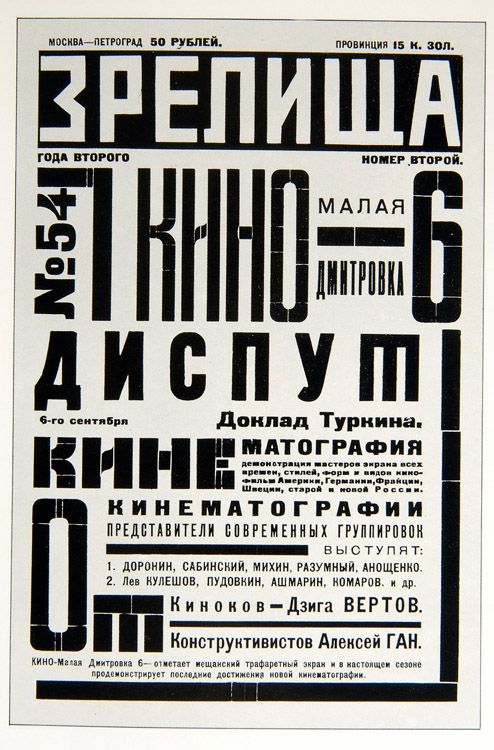
Советский леттеринг или шрифтовые композиции. Основные особенности | Русский Дизайн
Нас часто спрашивают: есть ли какие-то советские книги по советским рукописным шрифтам? На что мы неустанно отвечаем: нет, вернее были попытки что-то такое разработать Снарским, но безуспешные. А тем временем в этом нет ничего сложного и шрифты эти можно разбить на несколько групп. Конечно, новичку может показаться, что все они очень похожи, но это не так. Попробуем же сделать эту неблагодарную работу и рассмотреть каждую. Все названия будут условны, для усиления этой необходимой разницы между ними. Мы рассмотрим не все шрифты, но попытаемся выделить самые характерные и потому востребованные и в наше время.
1. Первая условная группа – «Классический». Такой шрифт больше всего напоминает рукописный. В частности он использовался в титрах кинофильма «Мимино». В остальном, чаще всего встречается в оформлении сталинской эпохи, выполняется тонкой кистью или пером.
2. Пользуется наибольшей популярностью, мы называем его «плакатным», т.к. выполнялся он в советские времена специальным плакатным пером представляющим собой плоскую металлическую пластинку и дающую толщину и остроту буквам.
Советский леттеринг или шрифтовые композиции. Основные особенности3. «Плакатный» жирный.
Советский леттеринг или шрифтовые композиции. Основные особенности4. «Округлый» шрифт. Такой мог встречаться на различных этикетках вин, на коробках шоколадных конфет и проч. Мог выполняться тонкой или средней колонковой кистью.
Советский леттеринг или шрифтовые композиции. Основные особенности5. «Неоновый». Чаще всего использовался в качестве вывесок универмагов, кинотеатров и проч. Эскизы такого могли выполняться обычной ручкой, реже пером.
Советский леттеринг или шрифтовые композиции. Основные особенности6. «Неоновый вертикальный». Применение такого, пожалуй, было даже шире, встречался и в книжках. Хотя с эстетической точки зрения он явно проигрывал первому.
7. «Промышленный». Применялся чаще всего для бытовой техники. Мог выполняться плакатным пером, однако с таким движением руки, чтобы толщина сохранялась одинаковой.
Советский леттеринг или шрифтовые композиции. Основные особенности8. «Плакатный прямой». Состоит из наклонных ровных полос и образующих буквы. Комбинированный шрифт по сути, часть выполняется плакатным пером, а какие-то буквы выводятся средней кистью.
Советский леттеринг или шрифтовые композиции. Основные особенности9. «Книжный». Распространение его было не таким широким, как у предыдущих. Это неудивительно, его очень сложно подвести под определение – рукописный. Такие шрифты встречались разве что в книжных иллюстрациях, титрах мультипликационных фильмов.
Дело в том, что воспроизвести его сразу не получится, какие-то детали придется доводить отдельно тонкой кистью, пером, ручкой.
Ну и нельзя не сказать о шрифтах, которым сложно дать какое-то определение, их следовало бы назвать декоративными, а некоторые из них, мы бы даже охарактеризовали, как шрифты с композиционными и прочими ошибками. А таких, между тем, не менее половины от встречающихся и по сей день на этикетках и вывесках. Но нельзя забывать и о том, что, скажем, тем рисунок и особенно живопись и отличаются от фотографии, тем и ценна она – некоторым несоответствием жизни, ее неизбежным искажением. Фотореалистичное же искусство многие профессионалы таковым не считают и это, пожалуй, справедливо. Так и шрифтовыми композициями занимаются чаще всего профессиональные художники. И порой даже нельзя объяснить, почему тот или иной шрифт прекрасен, сказывается профессиональное чутье.
Советский леттеринг или шрифтовые композиции.
Основные особенностиСоветский леттеринг или шрифтовые композиции. Основные особенностиСоветский леттеринг или шрифтовые композиции. Основные особенностиСоветский леттеринг или шрифтовые композиции. Основные особенностиСоветский леттеринг или шрифтовые композиции. Основные особенностиСоветский леттеринг или шрифтовые композиции. Основные особенностиСоветский леттеринг или шрифтовые композиции. Основные особенностиНу и попробуем ответить на вопрос, можно ли научиться леттерингу. Нет, нельзя, потому что слова такого нет, но можно научиться составлять шрифтовые композиции. Более того, убеждены, что все рассмотренные шрифты рано или поздно будут разработаны и доступны для общего пользования. Достаточно вспомнить, что шрифт «Кока-Кола» имеется в общем доступе со всеми заглавными и прописными буквами.
«Народная» типографика. Использование шрифтов в плакатах xx века [Курсовая №33781]
Содержание:
Введение
Хотя в наше время, по сравнению с прошлым веком, существует гораздо больше средств передачи информации, плакатная типографика до сих пор остается востребована. Во время нахождения человека за пределами жилища телевизионные, радио и интернет-каналы как правило становятся мало применимы, и в бой выходят плакатные объявления. Идя на работу, в спортзал или просто прогуливаясь, нам не спрятаться от пытливых взоров рекламных билбордов и социальных плакатов.
Хоть в наше время плакаты сильно изменились и часто выступают на электронных носителях, они все еще основываются правилах, заложенных в XX веке. Давайте же для начала посмотрим на историю плакатной типографии XX века
Глава 1История печатной рекламы в РоссииПервая печатная реклама появилась в газете “Санкт-Петербургские ведомости”, издававшийся академией наук в 1728 году.
В 1831 начала печататься одна их первых частных русских газет, стабильно издававшихся в течении много времени. Четыре полосы газеты были отданы под рекламу представлений и книг, но остальные полосы были пропитаны скрытой рекламой.
Дизайнер: Евгений Анфалов
Литейное производство: Киевский типолитейный завод (КТФ)
Дата выпуска: Июль 2021Предыстория: KTF, новое литейное производство, расположенное в Киеве и Ганновере, было задумано основателями Евгением Анфаловым и Олеся Гергун как типографская площадка на пересечении латиницы и кириллицы.Их дизайнерская миссия варьируется от поиска шрифтов-призраков из прошлого за железным занавесом до сотрудничества со старыми мастерами для преодоления разрыва между поколениями и сохранения знаний. KTF Compact — счастливый результат того, что Анфалов называет импровизированной сессией перерисовки советских визуальных артефактов.